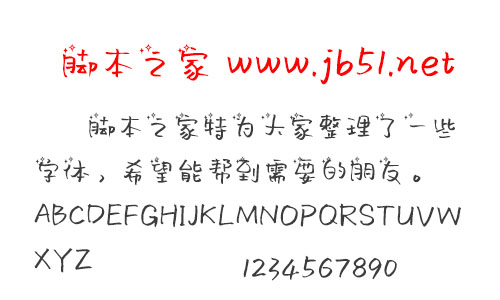
默陌豬事順意字體是默陌字庫(kù)推出的一款創(chuàng)意字體,書寫出的字體會(huì)有bulingbuling的星星裝飾圖案,非常有意思,可以適應(yīng)于報(bào)紙和雜志和書籍中常用字體, 海報(bào)、個(gè)性促進(jìn)品牌標(biāo)志設(shè)計(jì)、字體設(shè)計(jì)、等環(huán)境使用,歡迎喜歡默陌豬事順意字體的朋友前來(lái)下載使用。